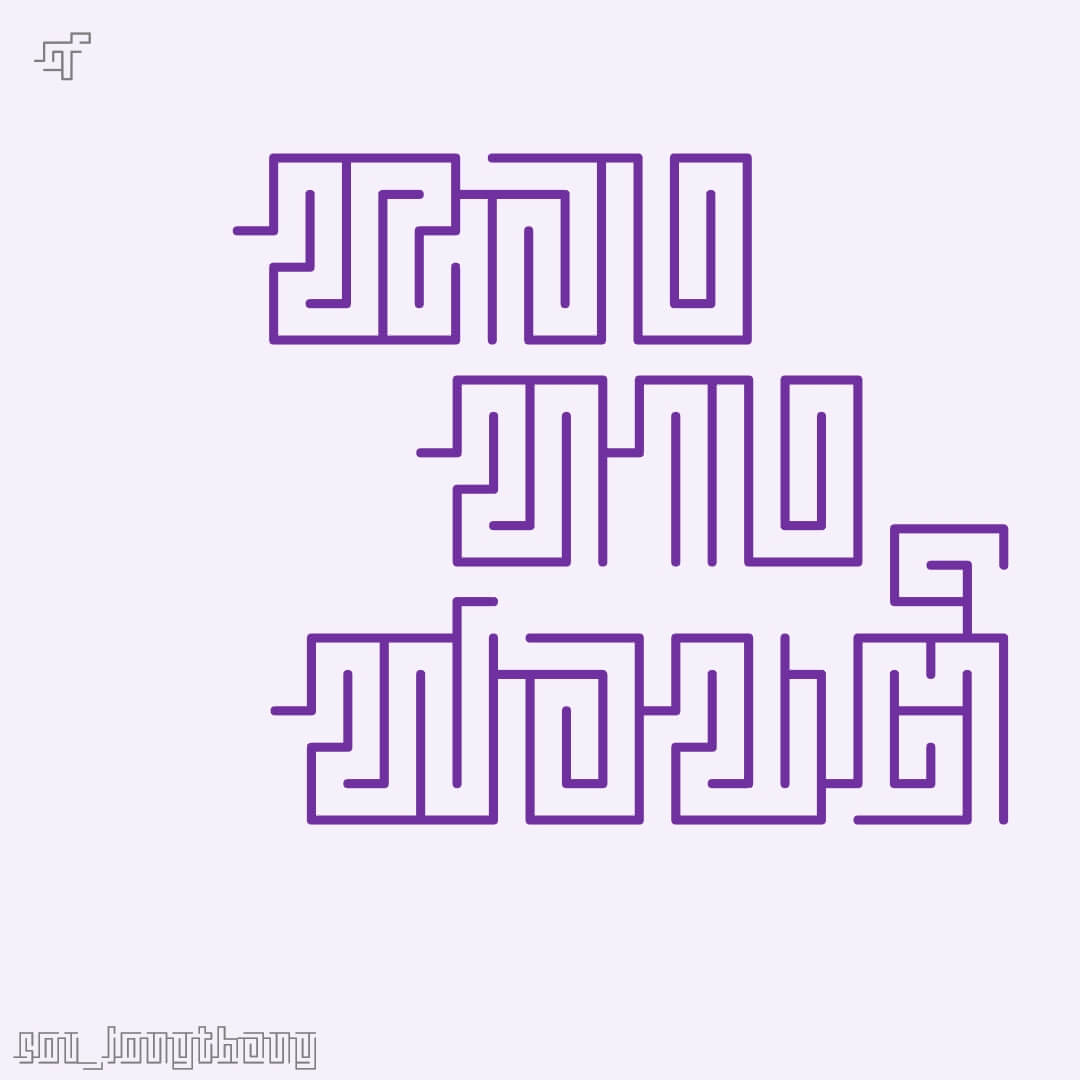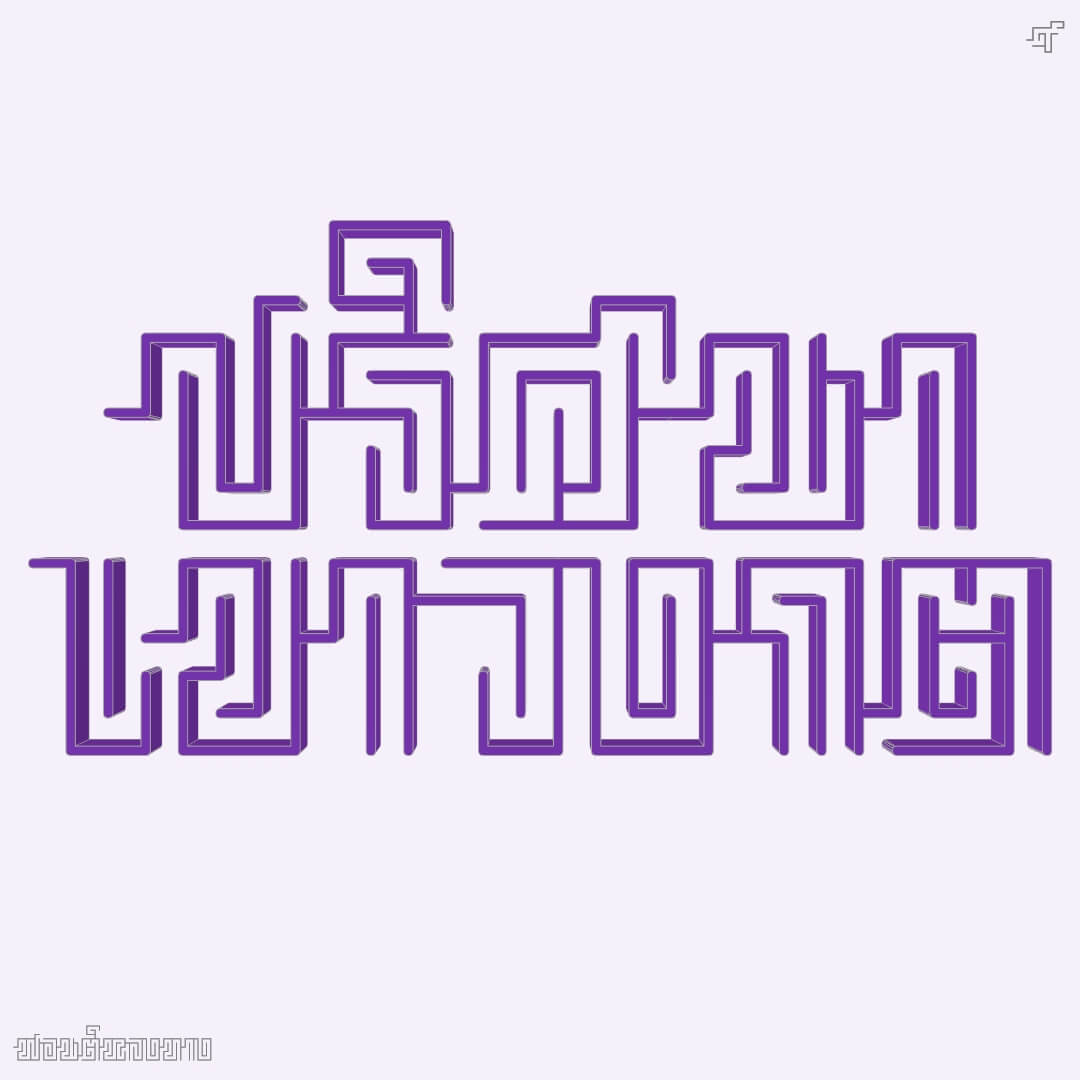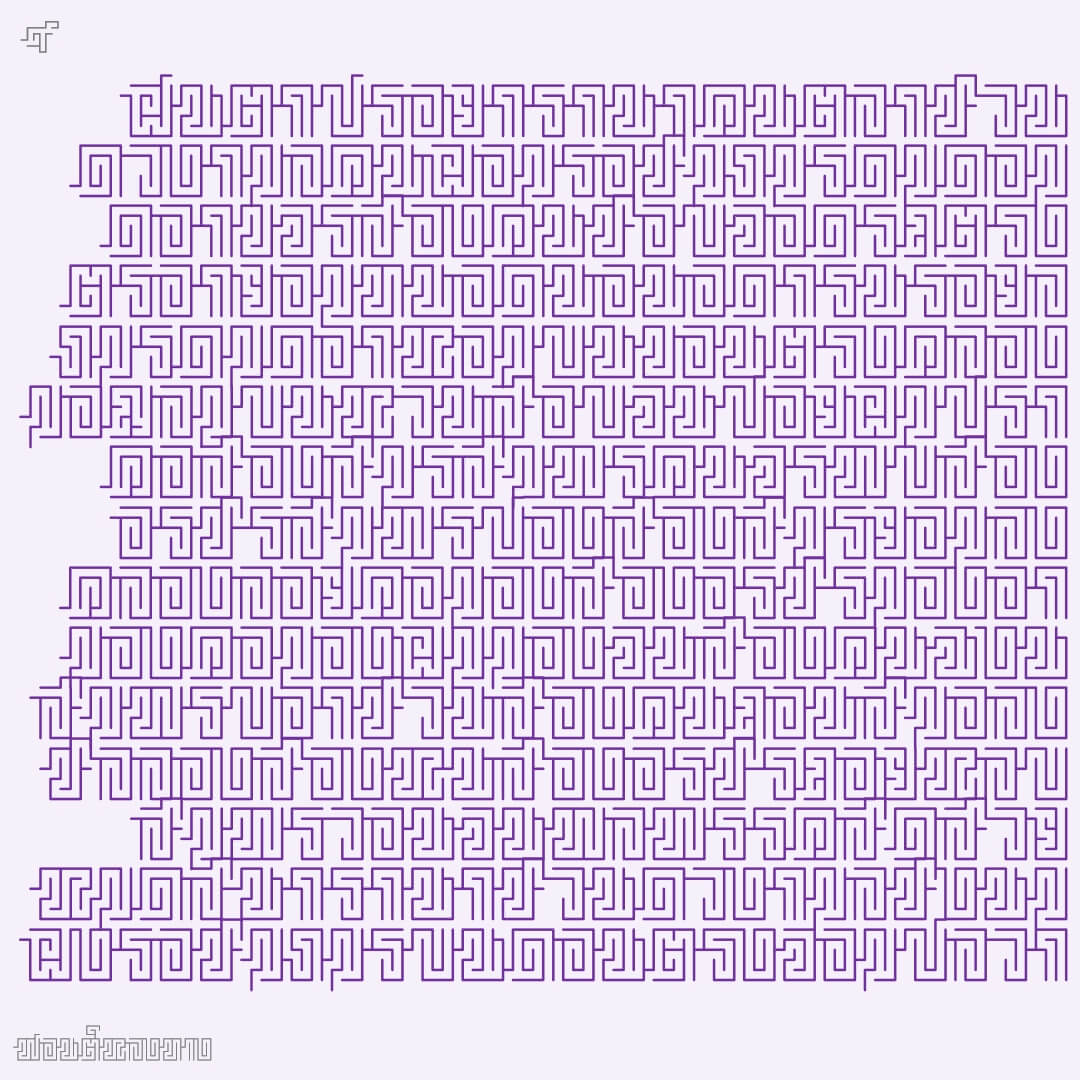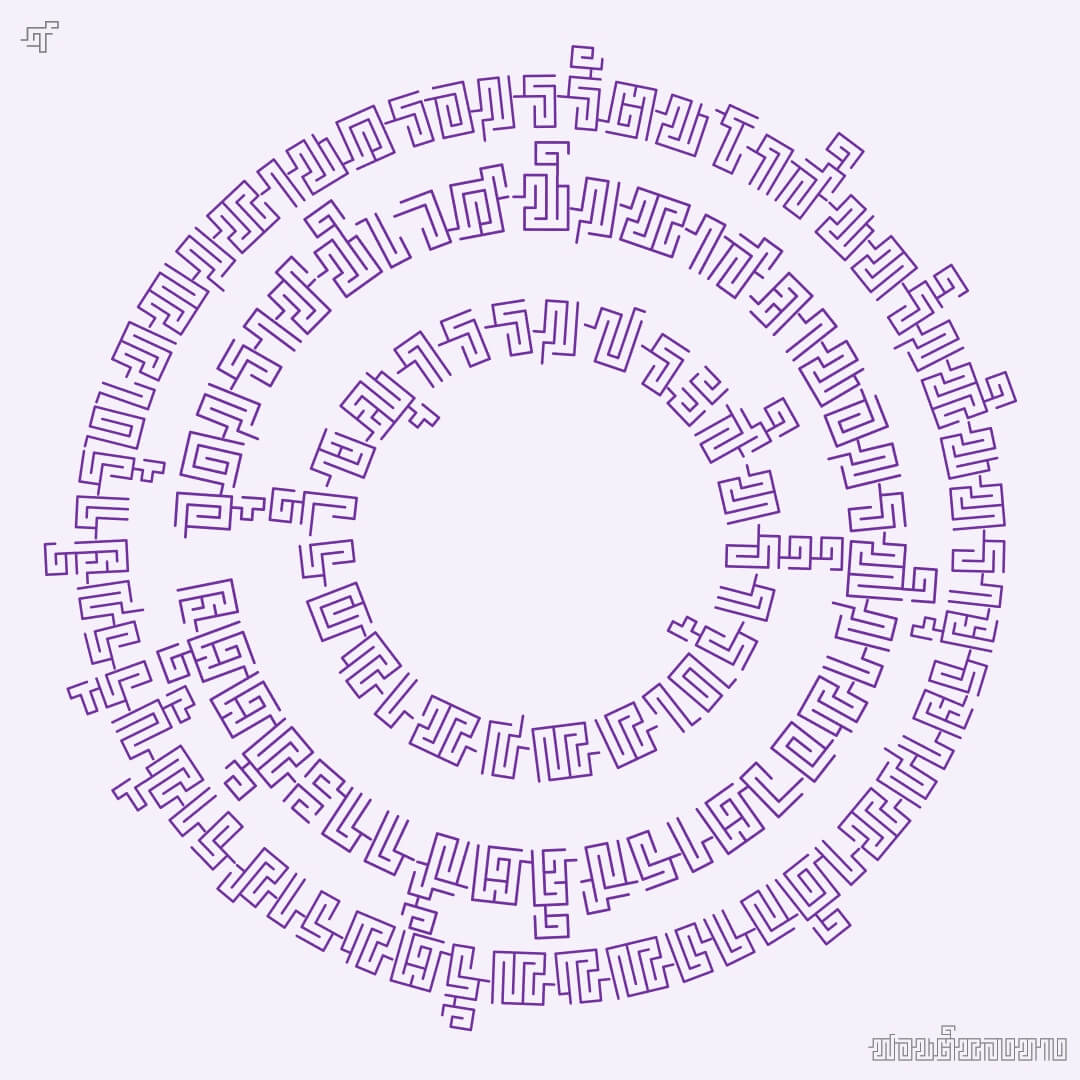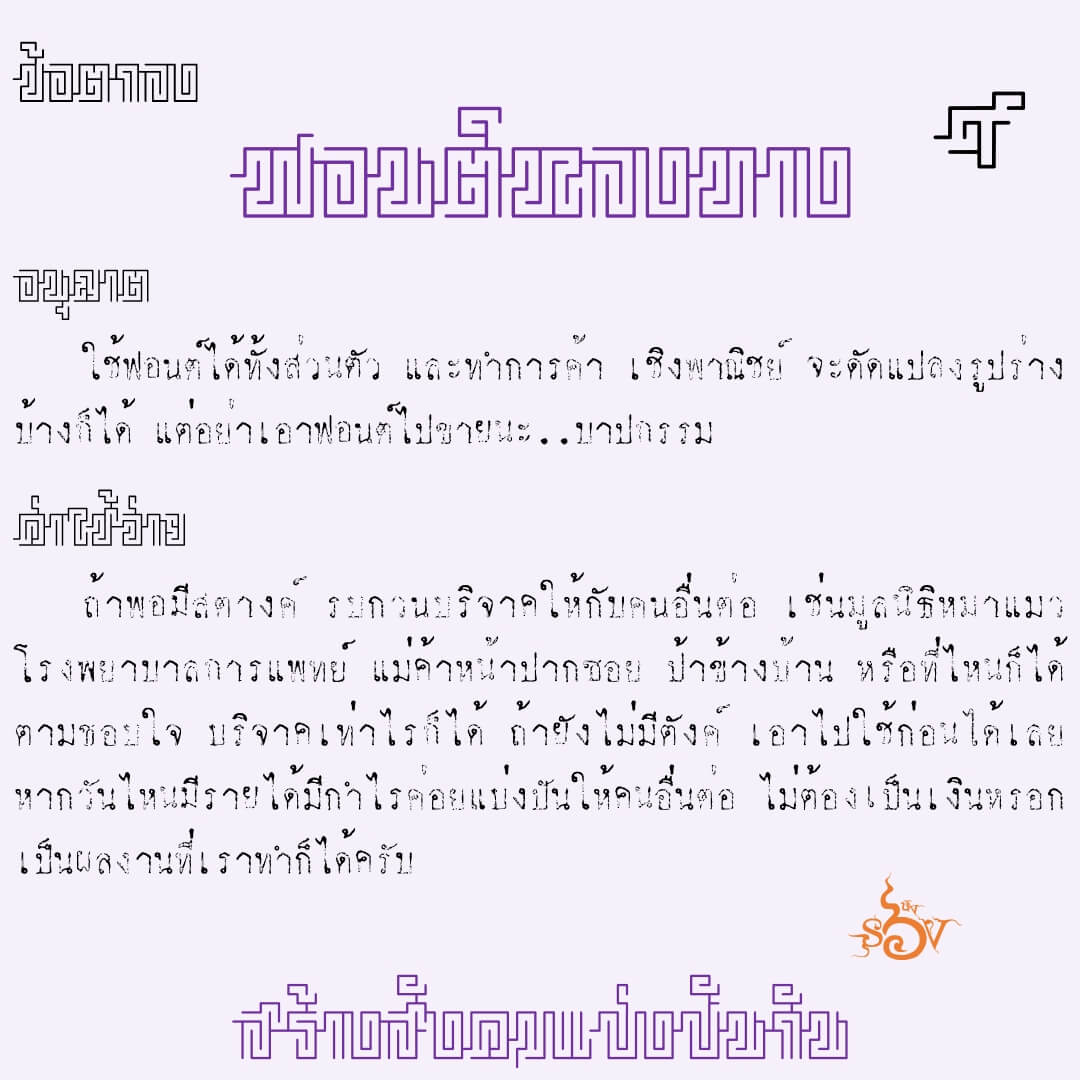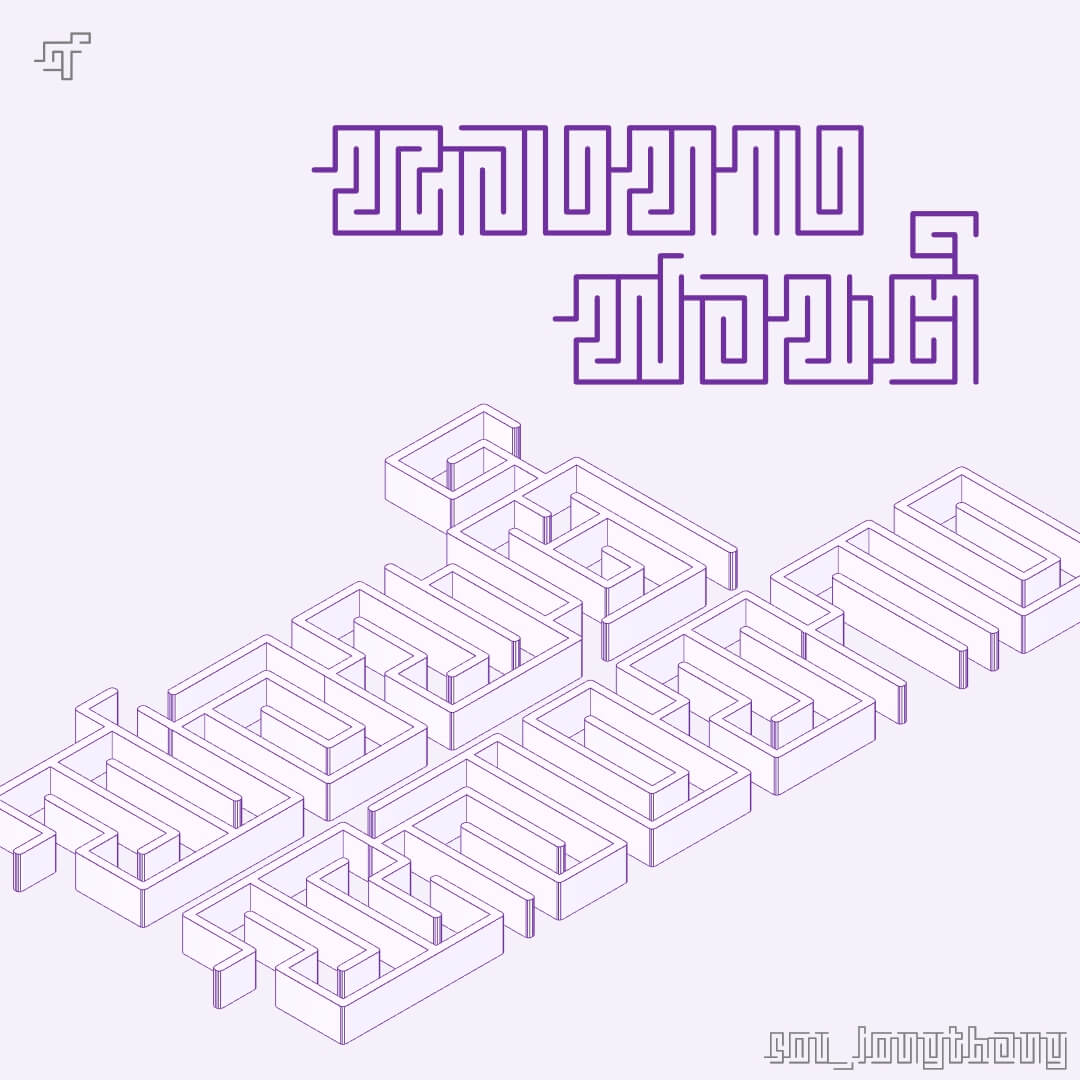
ฟอนต์หลงทาง เกิดจากเกมส์เขาวงกตที่เพื่อนกลุ่มฟอนต์เอามาเล่นจับคู่ฟอนต์ แต่เราดันเห็นเป็นตัวอักษร… หลอนมาก 55
เบื้องหลังการออกแบบ : ฟอนต์ หลงทาง
หลงทาง (SOV_LongThang)